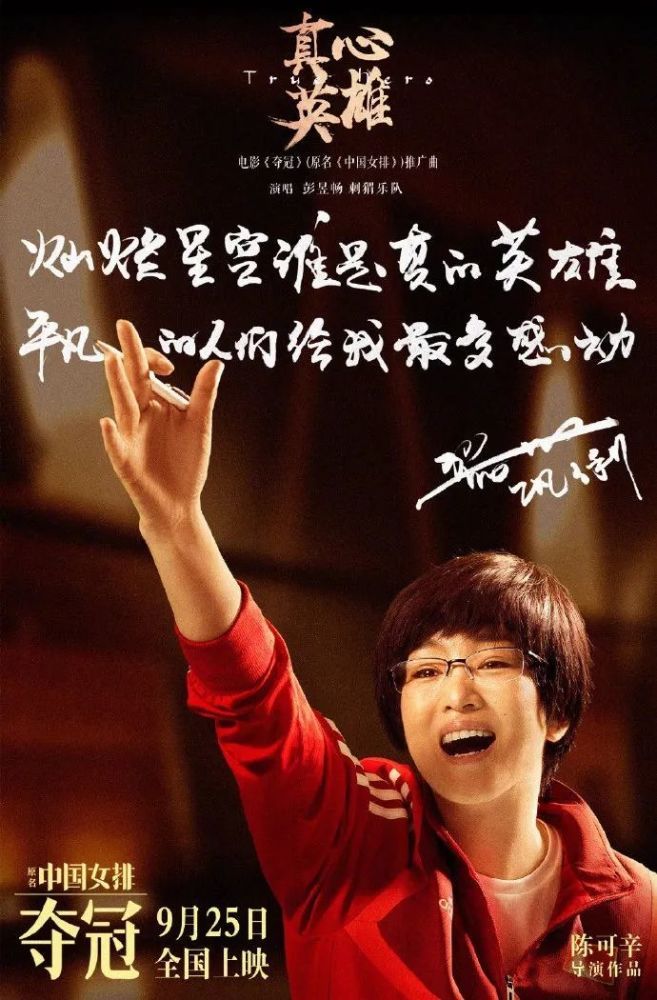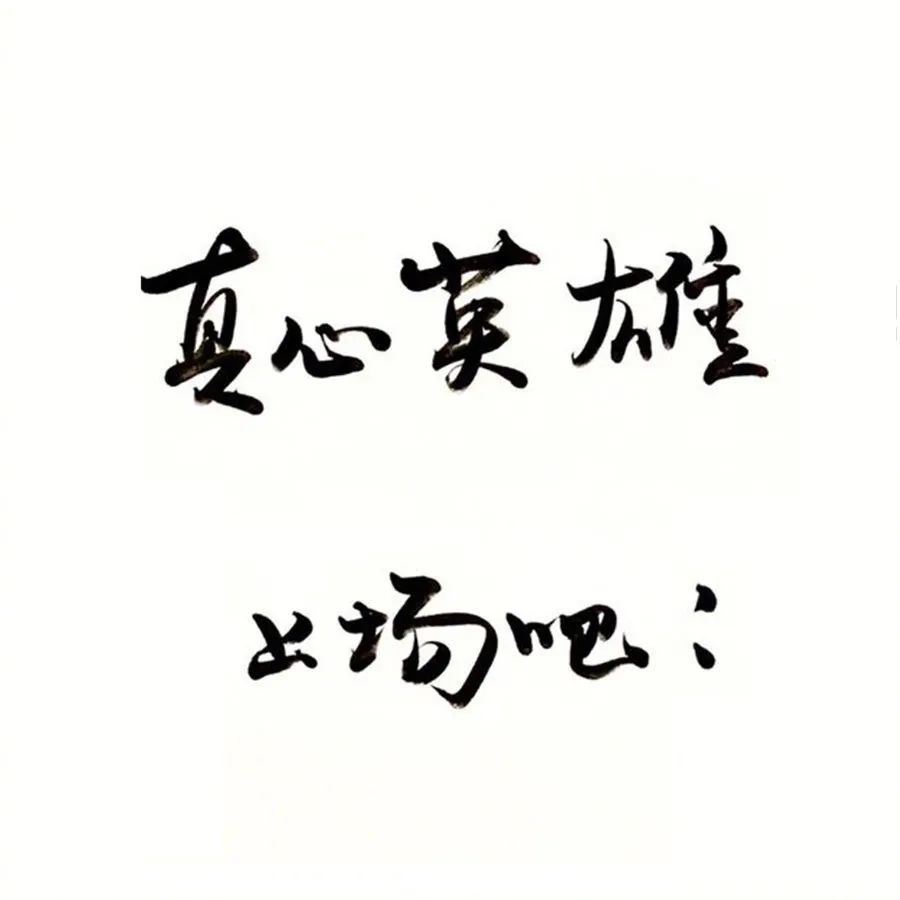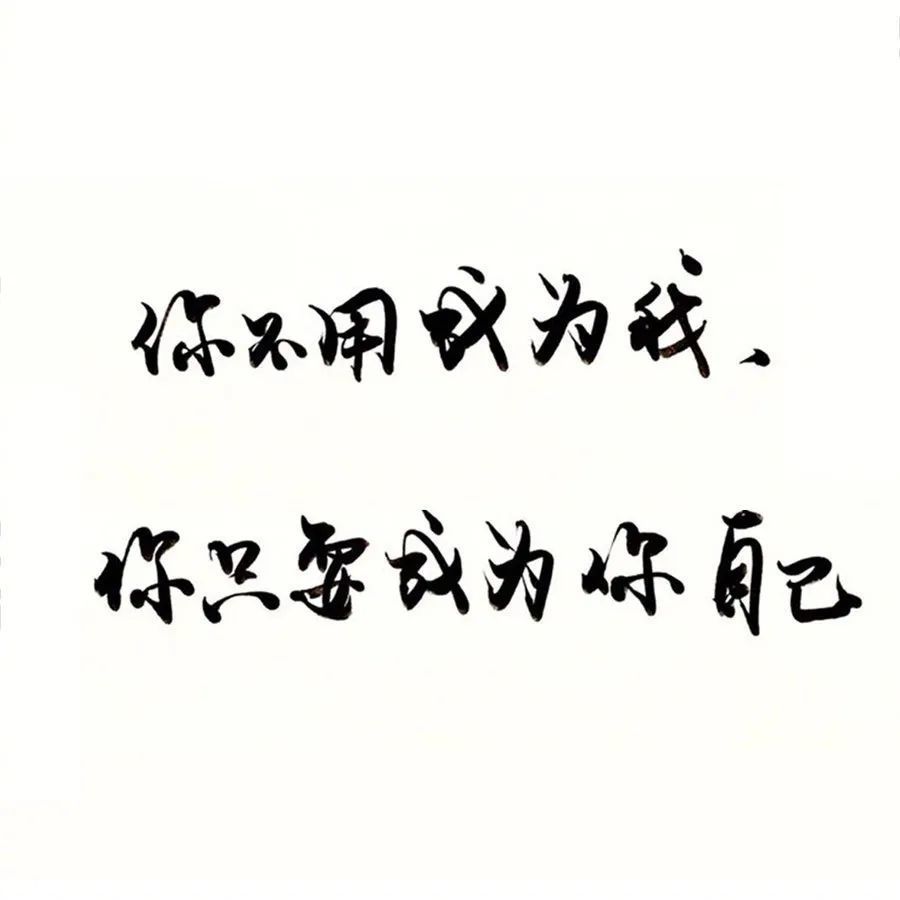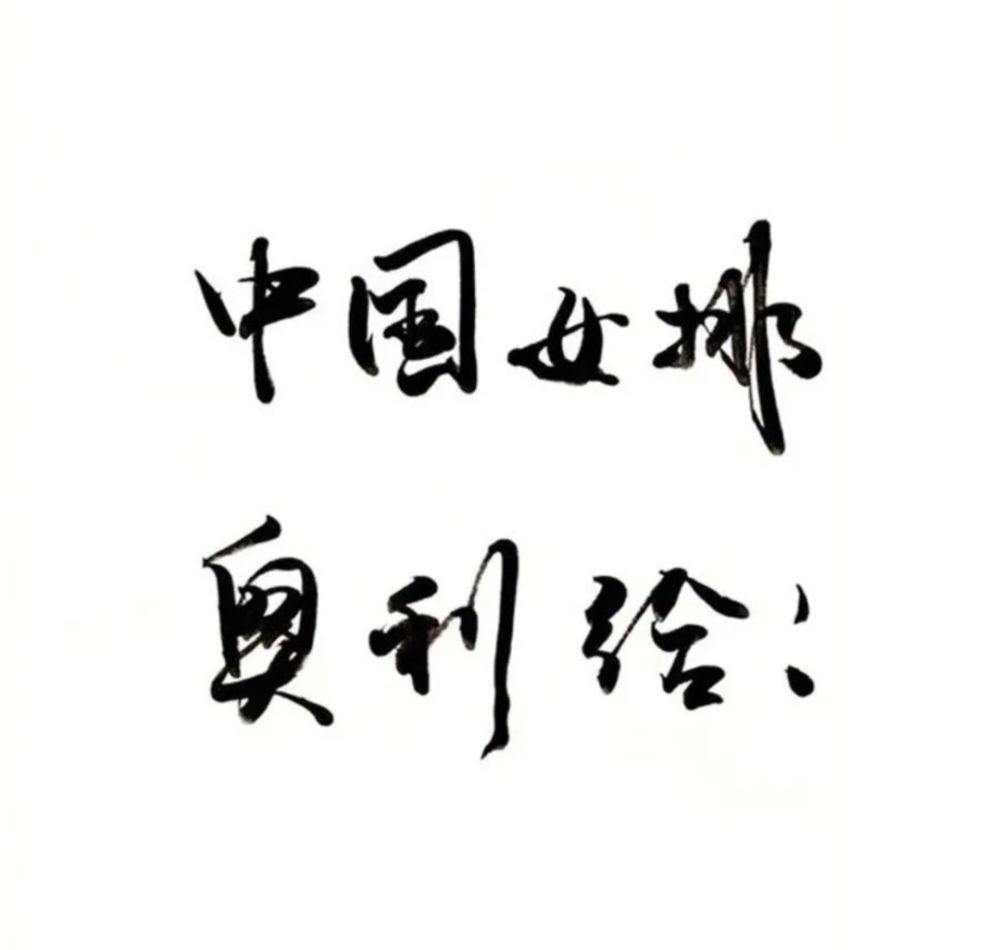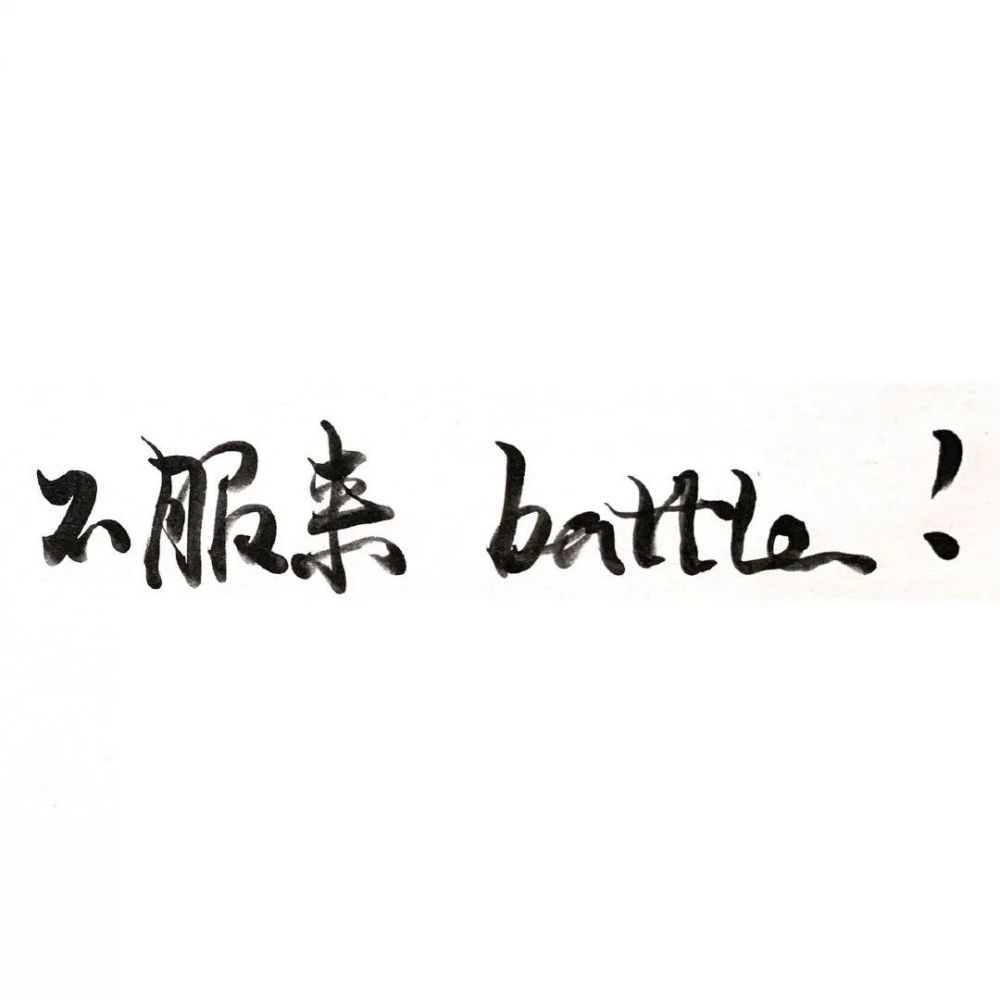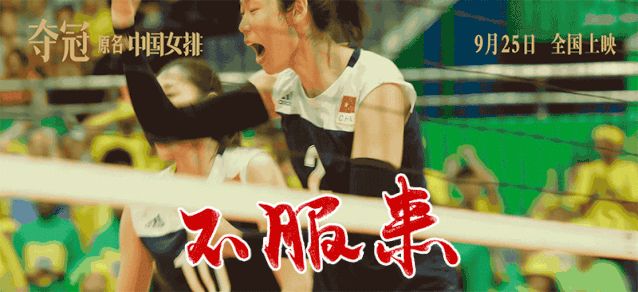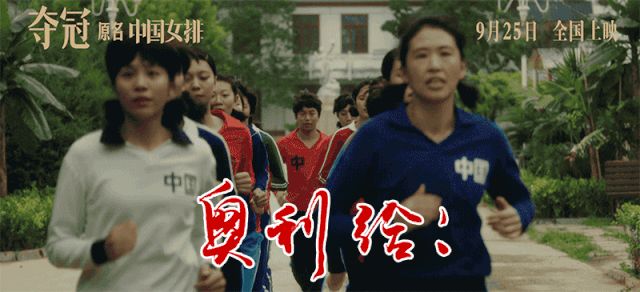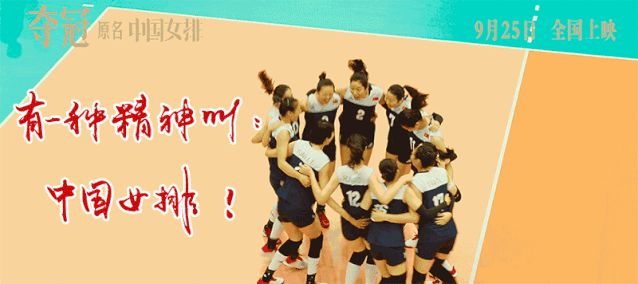
巩俐字体火了!铿锵有力,一笔一画都是对中国女排的热爱!网友:快出字体吧!
然而,“巩皇”还有另外一面——
在《夺冠》上映之际,制片方发布了一组海报,分别由主演巩俐、吴刚、白浪、彭昱畅等手写的《真心英雄》歌词,为电影的上映加油助威。
而巩俐不仅写了歌词,更写下了一组助威口号。
有一种精神叫:中国女排!
真心英雄上场吧!
你不用成为我,你只要成为你自己。
中国女排奥利给!
不服来battle!
字体铿锵有力,掷地有声,一笔一画都是对中国女排的热爱!#巩俐字体#这一话题也因此登上微博的热搜榜。
值得注意的是,巩俐写下了不少网络流行词汇,如“奥利给”、“不服来battle”、“瑞思拜”等等,生动又接地气,让大家倍感亲切。
对此,许多网友纷纷表达了自己的喜爱:
“巩俐老师的字太好看了”
“字体完全展现出了巩俐和郎平的霸气”
“好难想象巩俐写出奥利给!”
甚至有网友发出呼吁:巩老师快出字体吧!